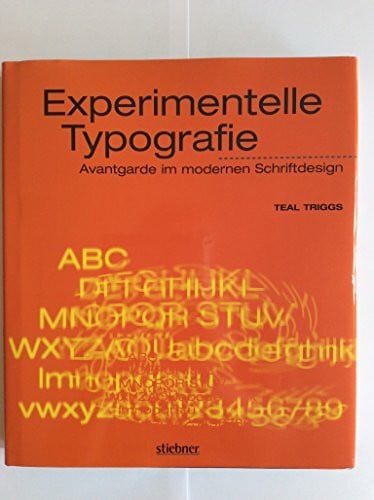
Experimentelle Typographie. Avantgarde im Schriftdesign
"Experimentelle Typographie. Avantgarde im Schriftdesign" ist ein Buch, das sich mit der innovativen und unkonventionellen Welt der Schriftgestaltung beschäftigt. Es beleuchtet die Entwicklung und Bedeutung avantgardistischer Ansätze im Bereich der Typographie. Das Buch untersucht, wie Designer durch kreative Experimente traditionelle Grenzen überschreiten und neue visuelle Ausdrucksformen schaffen. Dabei werden verschiedene Beispiele aus der Geschichte und Gegenwart vorgestellt, die zeigen, wie experimentelle Typographie zur künstlerischen und kulturellen Bereicherung beiträgt. Der Leser erhält Einblicke in die Techniken und Konzepte, die hinter diesen kreativen Prozessen stehen, sowie in die Auswirkungen auf Designtrends und Kommunikationsstrategien.